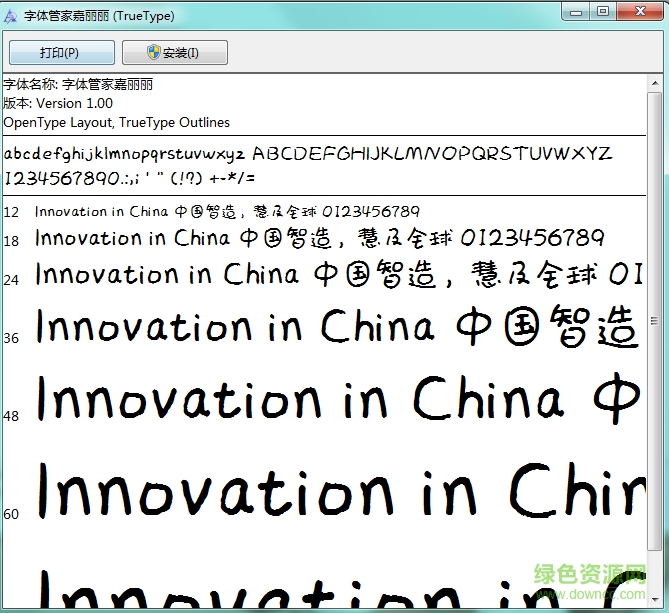
管家嘉麗麗體是一款網(wǎng)友制作的卡通字體,稚嫩秀氣的字形給人以童真童趣的美感,恣意活潑的手寫體風(fēng)格讓人躍然成趣,綠色資源網(wǎng)免費推薦!
嘉麗麗體娟秀簡潔,是出自字體管家的卡通藝術(shù)字體,可適用于平面設(shè)計、排版印刷、廣告創(chuàng)意等領(lǐng)域。